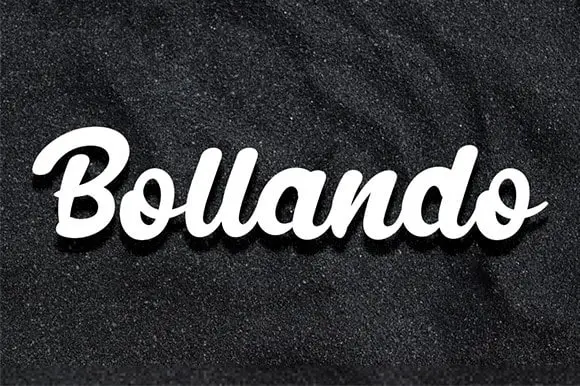
Bollando Bold Script Font – Download Grátis
A Bollando Bold Script Font é uma adição fascinante ao acervo das fuentes de letras escritas à mão. Ela surge em um momento onde as pessoas buscam expressar algo único e elegante, seja através do design de ambientes urbanos ou da personalização dos mais variados projetos. Suavemente bold, a Bollando apresenta uma graça única que se adapta perfeitamente para aplicações como postes na rua, convites de casamento, logos para publicidade nas redes sociais, embalagens e designs de produtos, etiquetas, logotipos de fotografias ou mesmo gráficos watermark. O seu charme autêntico se encaixa perfeitamente em todas as ocasiões que buscam uma pitada de personalização na sua identidade visual. A Bollando é um recurso valioso para aqueles designers buscando a perfeita mistura entre elegância e originalidade, disponível agora para ser integrado em seu próximo projeto. Ela está especialmente indicada para os trabalhos que requerem uma mão escritora de verdade.